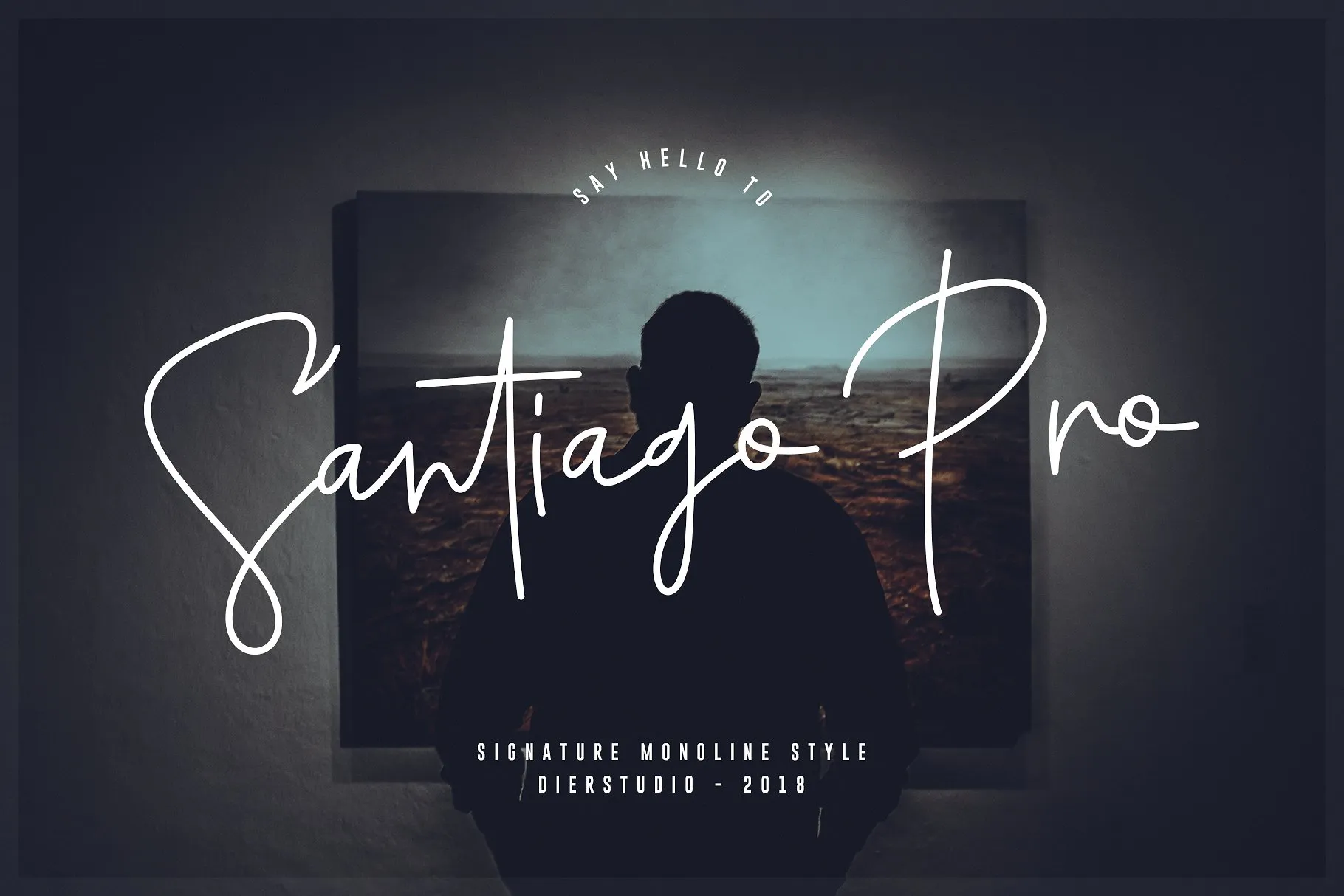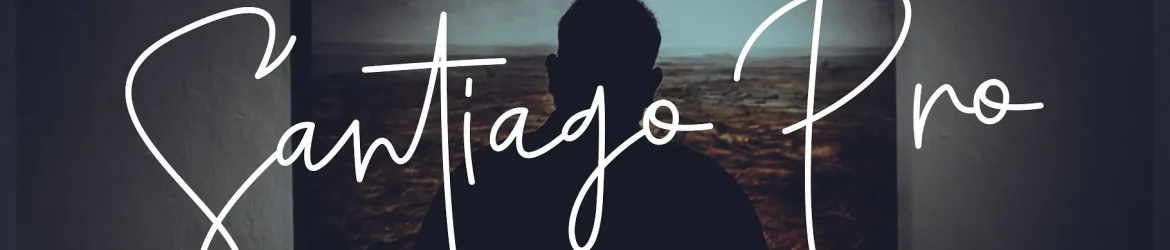
A fonte ‘Santiago Pro Signature Font’ é perfeita para designers que buscam uma fonte que remete diretamente ao mundo do design de mão escrita natural. Ela foi projetada pelo designer Hamilton e apresenta um estilo monolíneico, o que a torna uma opção ideal para diversas aplicações gráficas. Com 23 ligaturas incorporadas e alguns ajustes estilísticos, esta fonte é perfeita tanto para designers profissionais quanto para aqueles com mais experiência. Seu estilo natural confere aos projetos um toque de autenticidade, tornando-a uma escolha ótima para aplicações como branding, logomarcas, decoração de casamentos e redes sociais, publicidades, embalagens de produtos, etiquetas, fotografia, marcas digitais e até mesmo convites e material de papelaria. Santiago Pro Signature Font é uma escolha inteligente para designers que desejam incluir em seus projetos um toque autêntico e criativo. Seja você um profissional ou um designer iniciante, esta fonte oferece uma variedade de opções que farão do seu projeto um diferencial único.